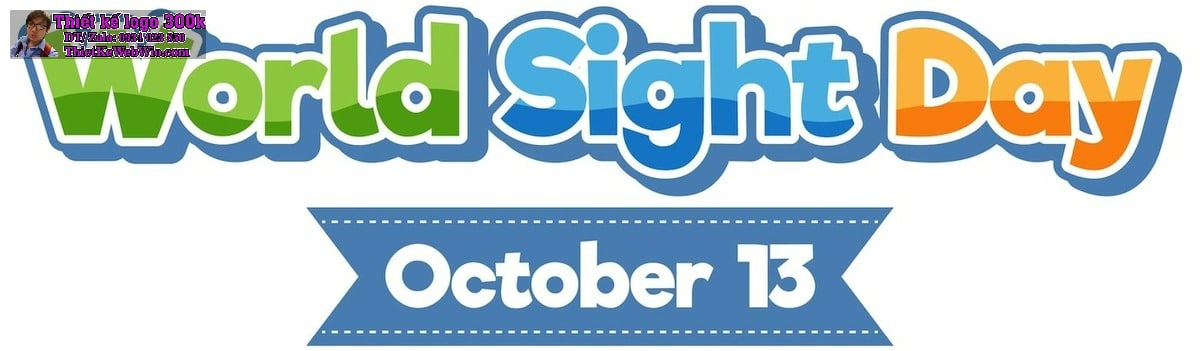
Trong việc tạo dựng một profile chuyên nghiệp, font chữ đóng vai trò quan trọng trong việc truyền tải thông điệp và thể hiện phong cách của thương hiệu. Việc chọn lựa font chữ trong thiết kế profile không chỉ cần phù hợp với hình ảnh doanh nghiệp mà còn phải đảm bảo dễ đọc và thu hút. Trong bài viết này, chúng ta sẽ cùng tìm hiểu về vai trò, tầm quan trọng và cách lựa chọn font chữ trong thiết kế profile chuyên nghiệp.
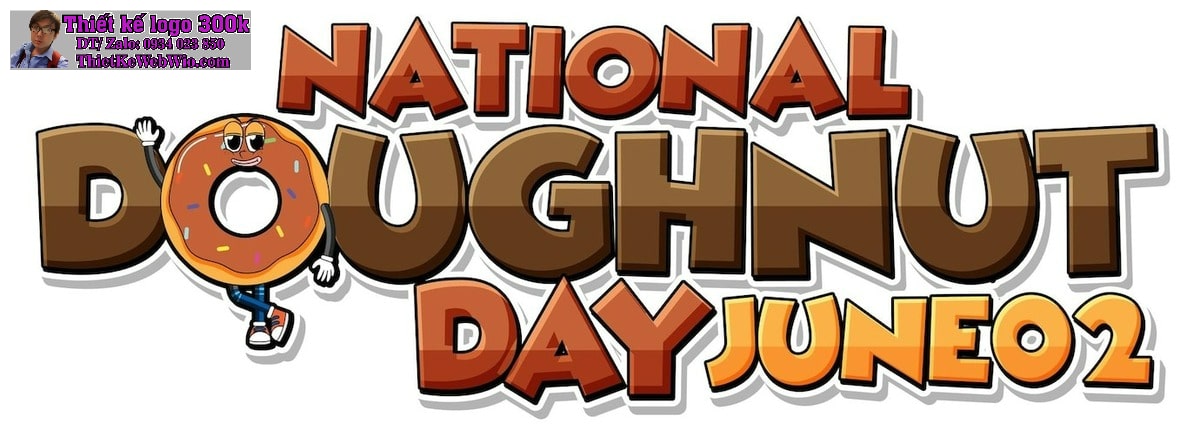
1. Vai trò của font chữ trong thiết kế profile
Font chữ là yếu tố cơ bản nhưng mang tính quyết định đối với sự thành công của một thiết kế. font chữ trong thiết kế profile giúp truyền đạt thông điệp một cách rõ ràng và trực tiếp đến khách hàng. Một font chữ phù hợp có thể tạo cảm giác chuyên nghiệp, gần gũi hoặc sáng tạo, tùy thuộc vào lĩnh vực và phong cách mà doanh nghiệp hướng tới.
Trong thiết kế profile, font chữ không chỉ giúp hiển thị nội dung mà còn tạo nên tính thẩm mỹ tổng thể của tài liệu. Một font chữ được chọn lựa cẩn thận sẽ giúp người xem dễ dàng tiếp cận thông tin, từ đó gia tăng sự thu hút và ấn tượng đối với doanh nghiệp.
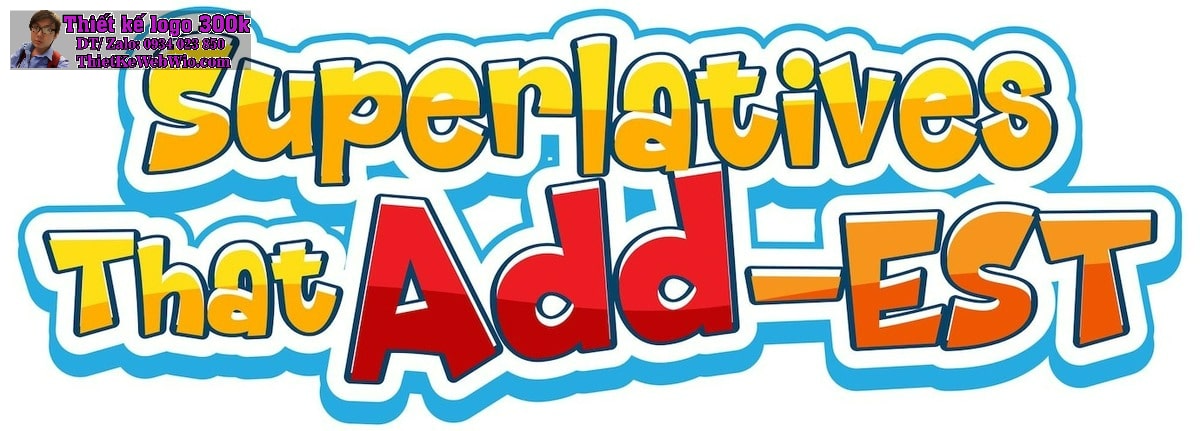
2. Tại sao việc lựa chọn font chữ trong thiết kế profile là quan trọng?
Lựa chọn font chữ trong thiết kế profile là một bước không thể bỏ qua vì nó ảnh hưởng trực tiếp đến cách mà khách hàng cảm nhận về thương hiệu. Một font chữ sai lệch có thể khiến doanh nghiệp trông thiếu chuyên nghiệp hoặc khó tiếp cận. Ngược lại, một font chữ được lựa chọn kỹ lưỡng sẽ giúp nâng cao giá trị thương hiệu, tăng cường sự tin cậy từ phía khách hàng.
font chữ trong thiết kế profile không chỉ đơn thuần là yếu tố hình ảnh mà còn góp phần xây dựng nhận diện thương hiệu. Khi một font chữ được sử dụng xuyên suốt trong các tài liệu và truyền thông của doanh nghiệp, nó sẽ giúp tạo ra sự đồng bộ và thống nhất, giúp thương hiệu dễ dàng được nhận diện.
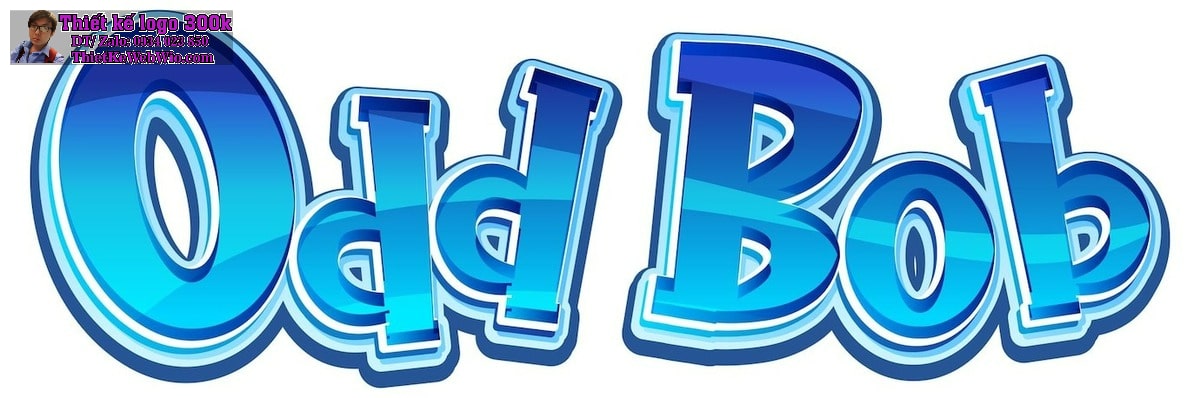
3. Các loại font chữ trong thiết kế profile phổ biến
Khi nhắc đến font chữ trong thiết kế profile, có nhiều lựa chọn khác nhau phù hợp với từng mục tiêu và phong cách thiết kế. Dưới đây là một số loại font chữ phổ biến và thường được sử dụng trong thiết kế profile:
– Font Serif: Đây là loại font chữ cổ điển với các nét chân tại đầu và cuối chữ cái. Nó thường mang lại cảm giác trang trọng, chuyên nghiệp và được sử dụng nhiều trong các lĩnh vực như tài chính, giáo dục hay luật pháp.
– Font Sans Serif: Là loại font chữ trong thiết kế profile không có các nét chân, mang đến sự hiện đại, đơn giản và dễ đọc. Font Sans Serif phù hợp với các thiết kế trẻ trung, sáng tạo hoặc công nghệ.
– Font Script: Đây là loại font chữ viết tay, thường được sử dụng trong các thiết kế đòi hỏi sự mềm mại, lãng mạn hoặc nghệ thuật.
Mỗi loại font chữ trong thiết kế profile đều có đặc điểm và cảm xúc riêng, vì vậy việc lựa chọn loại font phù hợp là điều vô cùng quan trọng để đảm bảo tính thẩm mỹ và hiệu quả.
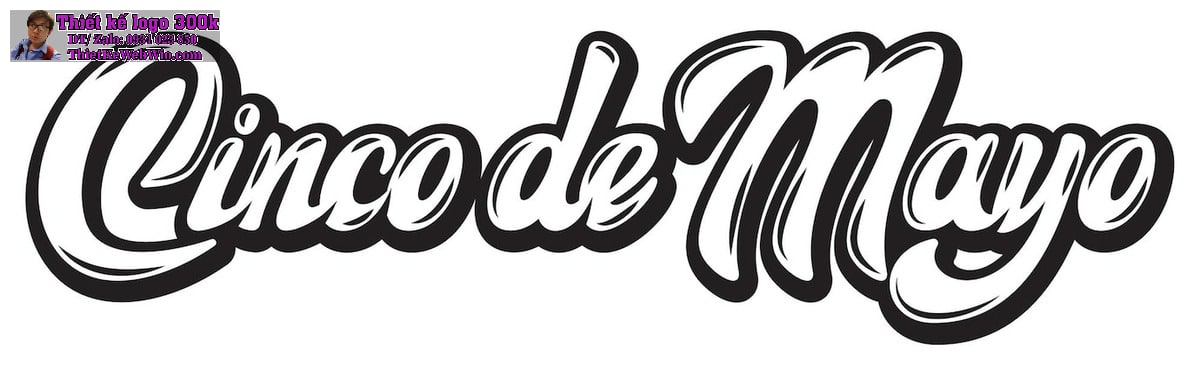
4. Nguyên tắc chọn font chữ trong thiết kế profile
Khi chọn font chữ trong thiết kế profile, cần tuân thủ một số nguyên tắc cơ bản để đảm bảo tính hiệu quả:
– Tính dễ đọc: Một profile cần phải truyền tải thông tin một cách rõ ràng và dễ hiểu. Do đó, font chữ cần phải dễ đọc và không gây nhầm lẫn cho người xem.
– Tương thích với thương hiệu: Font chữ phải phản ánh đúng phong cách và giá trị cốt lõi của doanh nghiệp. Một thương hiệu sáng tạo có thể sử dụng các font hiện đại, trong khi những doanh nghiệp truyền thống có thể lựa chọn các font serif cổ điển.
– Độ đồng bộ: Sử dụng quá nhiều loại font trong một profile có thể khiến thiết kế trông lộn xộn và thiếu chuyên nghiệp. Thay vào đó, chỉ nên sử dụng từ 1 đến 2 loại font chữ và đảm bảo chúng phù hợp với nhau.
Việc tuân thủ các nguyên tắc này giúp profile của doanh nghiệp trông chuyên nghiệp hơn và tạo được ấn tượng tốt với người xem
.
5. Cách kết hợp font chữ trong thiết kế profile
Trong một thiết kế profile, việc kết hợp nhiều font chữ có thể tạo ra sự đa dạng và hấp dẫn. Tuy nhiên, để tránh làm mất đi tính nhất quán và chuyên nghiệp, cần biết cách kết hợp đúng cách:
– Chọn font chữ chính và phụ: Một thiết kế profile thường có font chữ chính (dùng cho tiêu đề) và font chữ phụ (dùng cho nội dung). Font chữ chính cần nổi bật và thể hiện được phong cách của thương hiệu, trong khi font chữ phụ cần đơn giản và dễ đọc.
– Đảm bảo tính đồng bộ: Khi kết hợp các font chữ, cần đảm bảo chúng có sự liên kết về mặt thẩm mỹ, tránh việc lựa chọn các font quá khác nhau về phong cách, làm giảm tính nhất quán.
– Sử dụng kích thước font hợp lý: Ngoài việc chọn loại font, kích thước font cũng là yếu tố quan trọng. Tiêu đề và nội dung cần có sự phân cấp rõ ràng về kích thước để tạo điểm nhấn và dẫn dắt người xem theo trình tự mong muốn.
Việc kết hợp font chữ trong thiết kế profile một cách hài hòa sẽ tạo ra một tổng thể thu hút và giúp người xem dễ dàng tiếp cận thông tin.
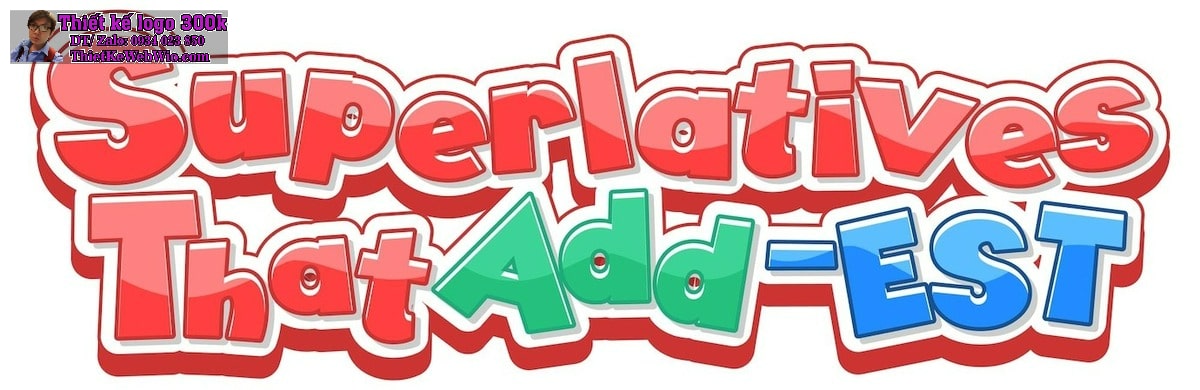
6. Lựa chọn font chữ trong thiết kế profile phù hợp với từng ngành nghề
Mỗi ngành nghề có những yêu cầu và đặc trưng riêng, vì vậy việc lựa chọn font chữ trong thiết kế profile cũng cần được cân nhắc kỹ lưỡng dựa trên lĩnh vực hoạt động của doanh nghiệp:
– Ngành tài chính và luật: Các font chữ serif trang trọng và cổ điển thường được ưa chuộng, mang lại cảm giác đáng tin cậy và chuyên nghiệp.
– Ngành công nghệ: Font chữ sans serif hiện đại, tối giản thường phù hợp với các doanh nghiệp công nghệ, thể hiện sự sáng tạo và tiên tiến.
– Ngành nghệ thuật và thời trang: Các font chữ script mềm mại hoặc các font mang tính nghệ thuật cao sẽ giúp profile trở nên nổi bật và thu hút.
Lựa chọn đúng font chữ trong thiết kế profile không chỉ giúp doanh nghiệp truyền tải thông điệp hiệu quả mà còn thể hiện phong cách và giá trị của thương hiệu một cách rõ ràng.
Kết luận:
font chữ trong thiết kế profile là yếu tố quan trọng giúp doanh nghiệp tạo dựng hình ảnh và truyền tải thông điệp đến khách hàng. Việc chọn lựa và kết hợp font chữ một cách phù hợp sẽ góp phần nâng cao giá trị thương hiệu và giúp doanh nghiệp thu hút sự quan tâm của đối tác, khách hàng tiềm năng. Đầu tư vào việc chọn font chữ trong thiết kế profile không chỉ giúp nâng cao tính thẩm mỹ mà còn gia tăng hiệu quả trong việc tiếp cận khách hàng.